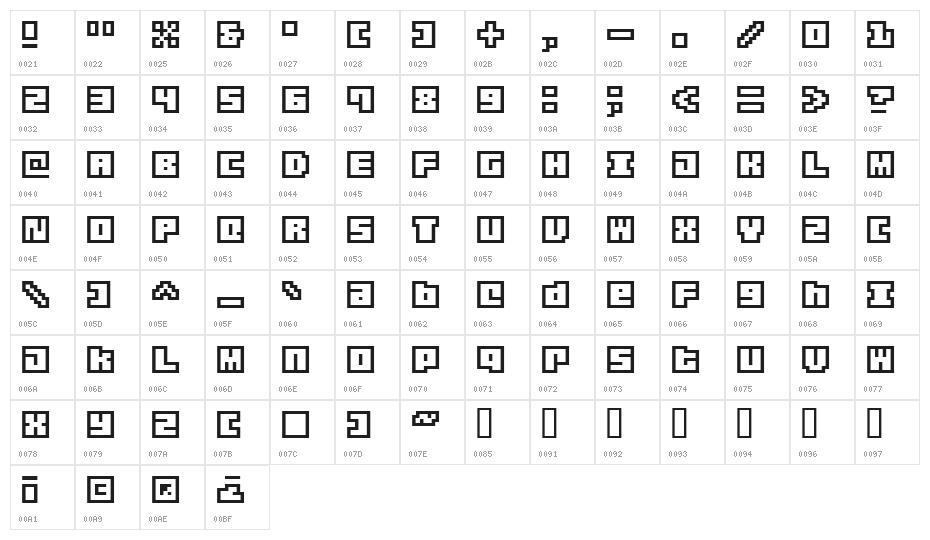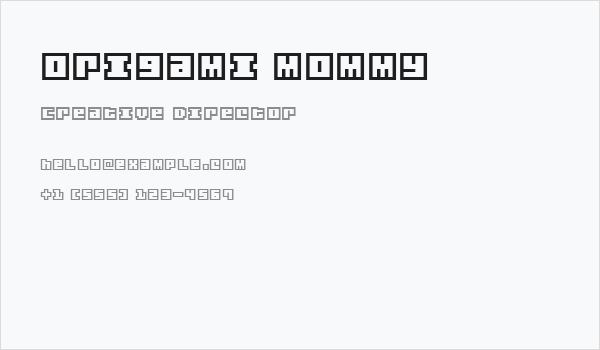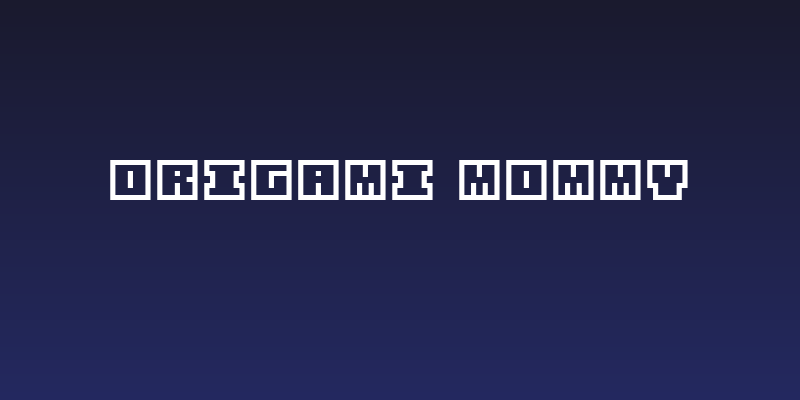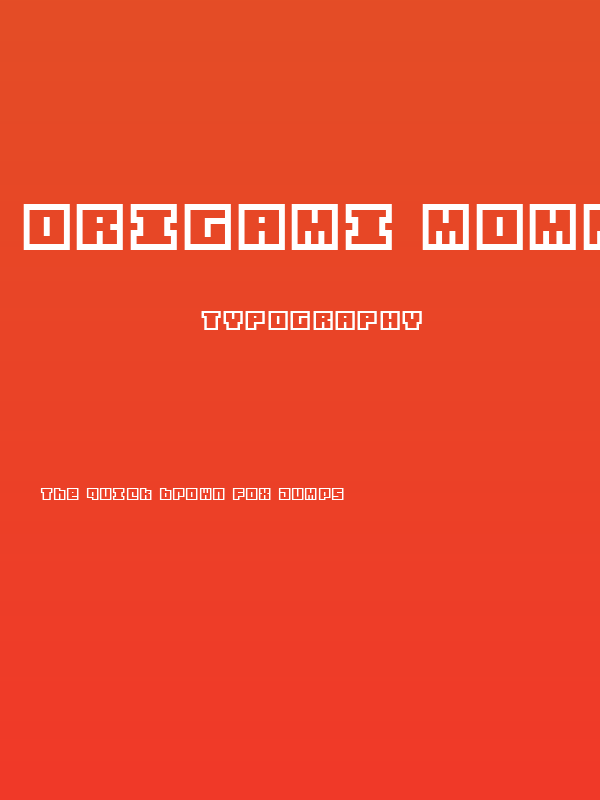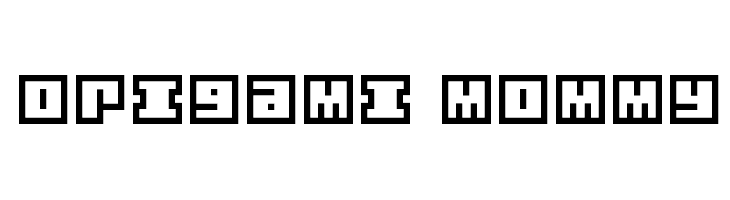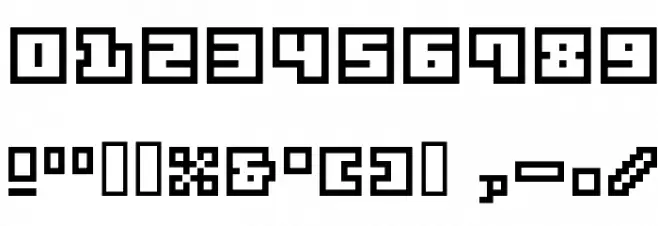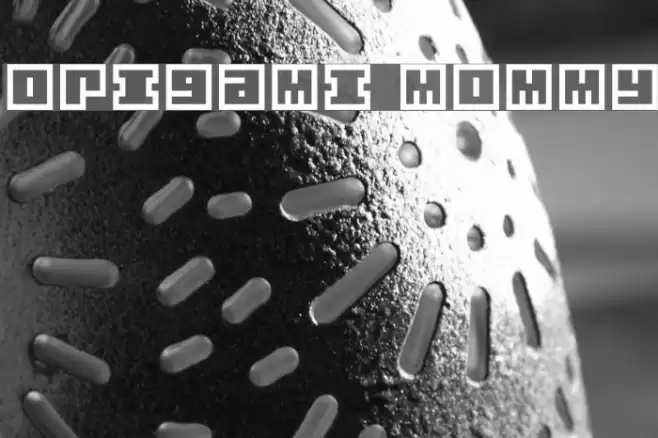
Origami Mommy Font
✎ Stencil
| Kategorien | Stencil |
| Gesamtstil | Retro, Geometric |
| Vorgeschlagene Projekte | Ideal for video game graphics, tech-themed posters, retro digital displays, and creative branding projects. |